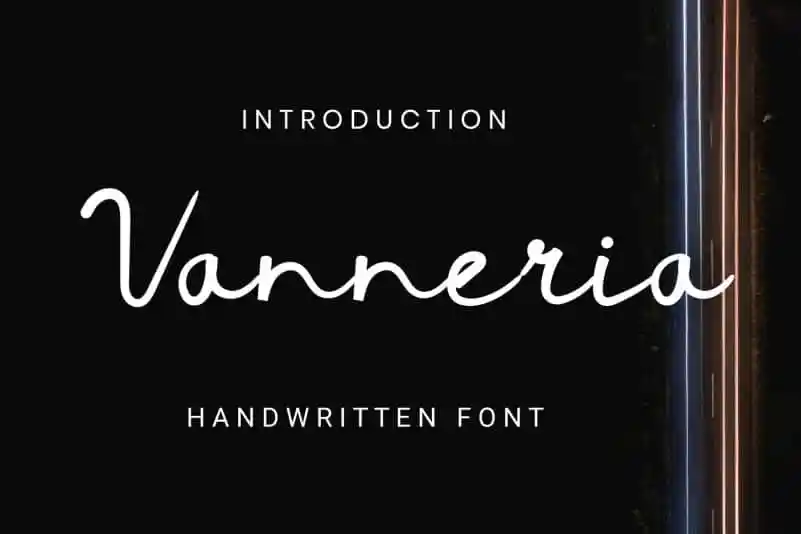
Vanneria Handwritten Font – Download Grátis
Vanneria Handwritten Font é uma linda fonte escrita a mão delicada e suave. Seu charme leve e nostálgico o torna ideal para muitas situações, criando um ar fresco e descontraído. Suas qualidades versáteis o tornam perfeito para transformar simples ideias em design de alta qualidade. Este é o tipo certo para quem valoriza a essência das artes gráficas, procurando por uma fonte que expressa uma pitada de serenidade e frescor. Vanneria Handwritten Font é mais do que apenas um recurso gráfico; ele é uma peça vital no seu projeto visual, tornando cada design único e envolvente.